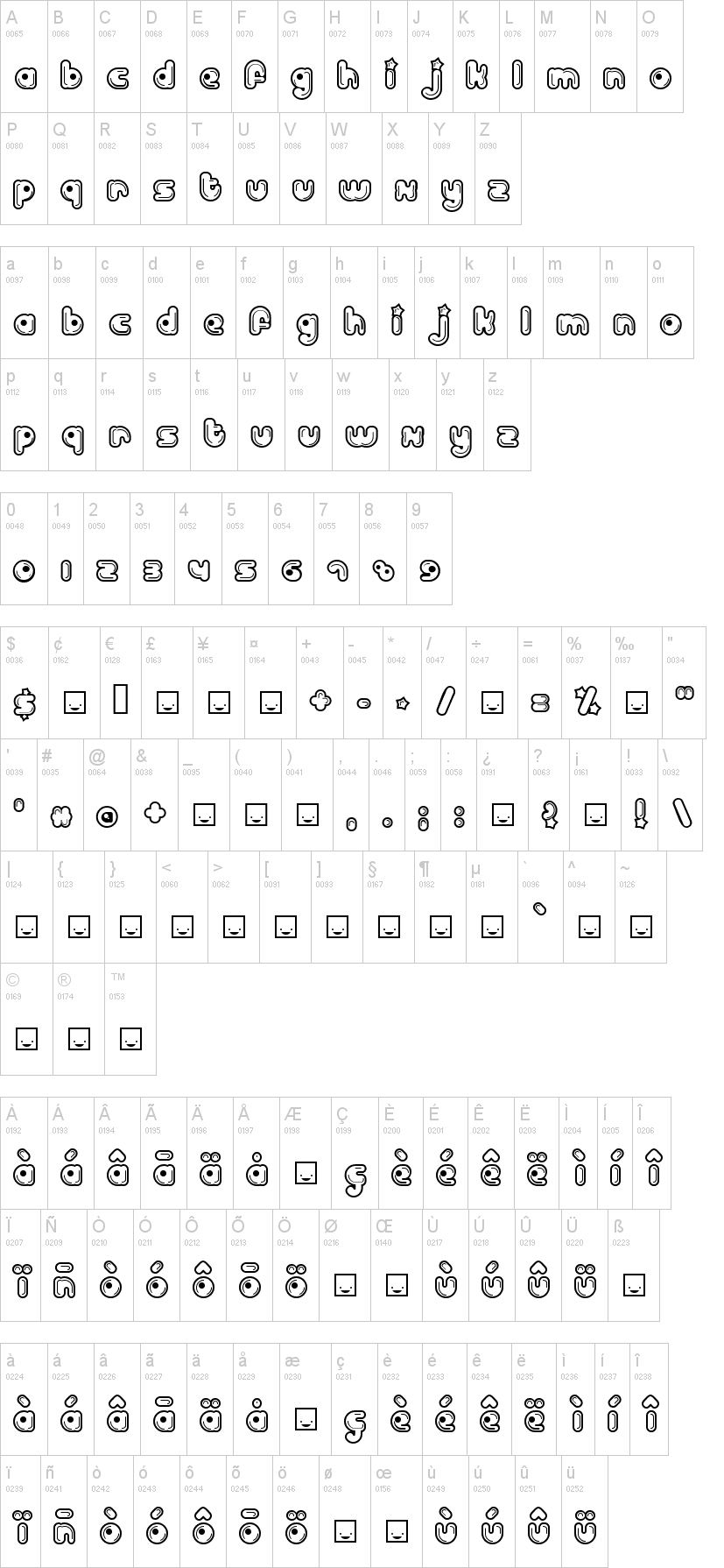
Billo Dream
Billo Dream是一款拥有轻快的线条和温暖的气息的字体,它是由著名的设计师Billo的设计团队创作的。这款字体有着柔和的外观,可以用于创作各种类型的设计,比如海报、标志、logo、品牌标识等。它还具有良好的可读性,可以让读者更容易理解文字内容,更加舒适地阅读。
Billo Dream是一款非常不错的手写艺术字体,具有很好的视觉感,适合于文化类的宣传设计、商业类品牌的广告和产品包装设计以及个性化文字排版等较多场景。